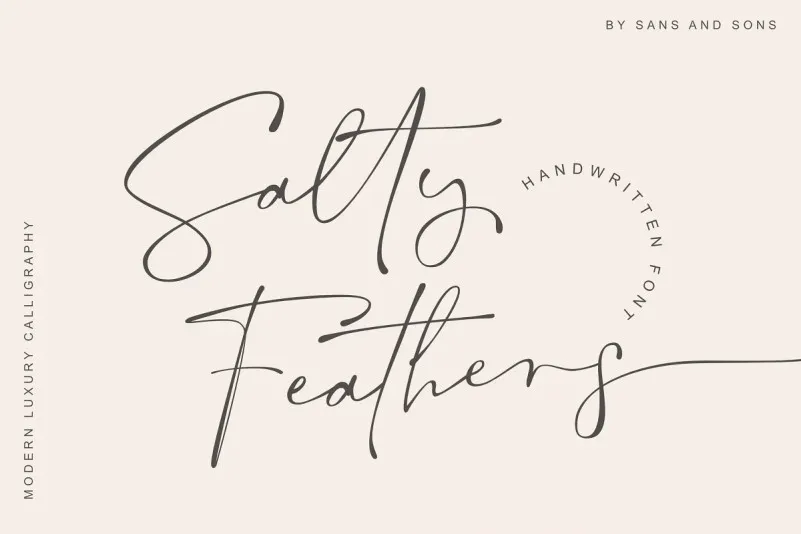
A Salty Feathers Font é uma escolha perfeita para quem busca um estilo romântico e elegante para seus projetos digitais, seja para criar identidades visuais, logo personalizados ou até mesmo cartões de convite. Essa fonte, desenvolvida pelo talentoso designer Sans & Sons na categoria de scripts, oferece uma textura orgânica e suave que imita o toque úmido da tinta quando escrito a mão. Com um mix de letras maiúsculas e minúsculas, símbolos multilingues, números, pontuação e alternativas adicionadas, esta fonte traz uma grande variedade de recursos para suas necessidades gráficas. Seu estilo moderno e elegante torna-o perfeito para qualquer projeto que exige um toque sofisticado, como branding, design de logotipos ou adesivos para cartões de convite. A Salty Feathers é uma ótima escolha para dar um toque único em sua próxima criação visual.